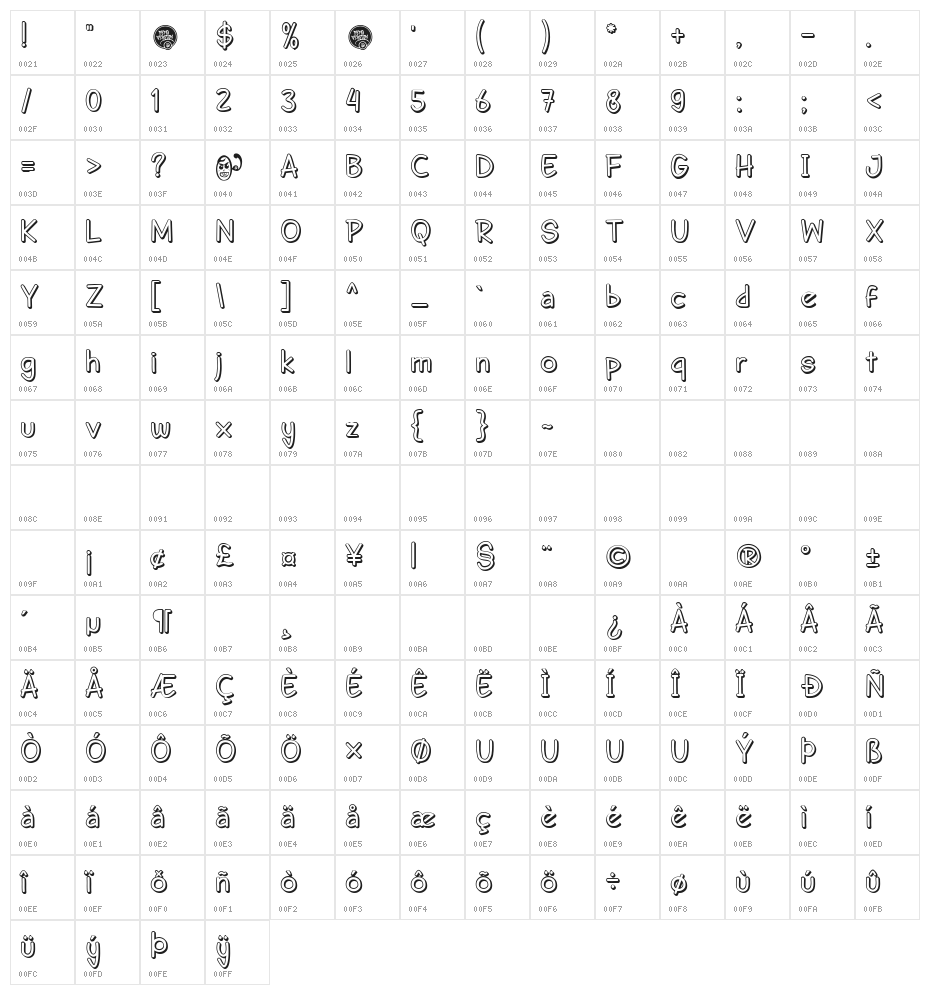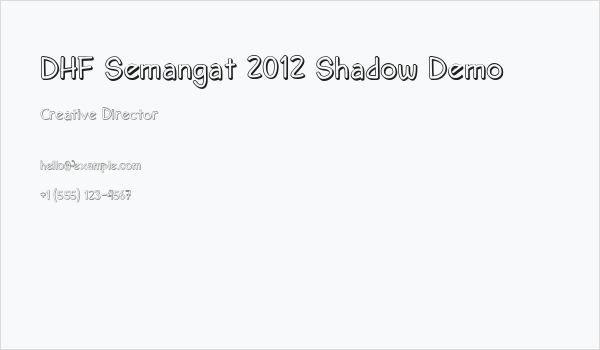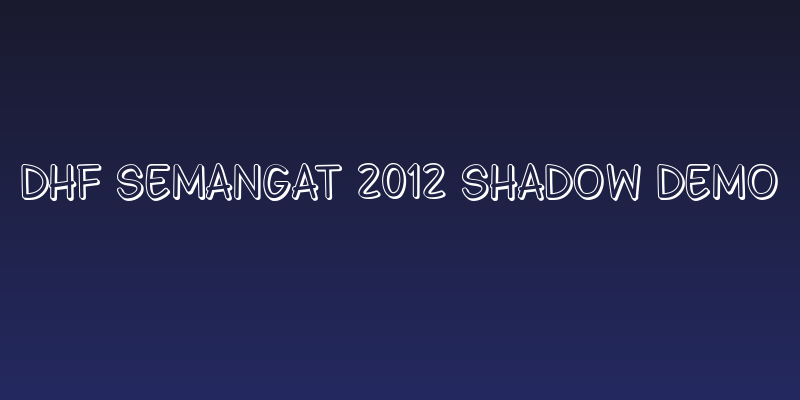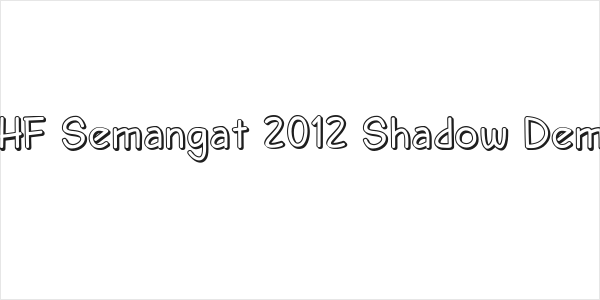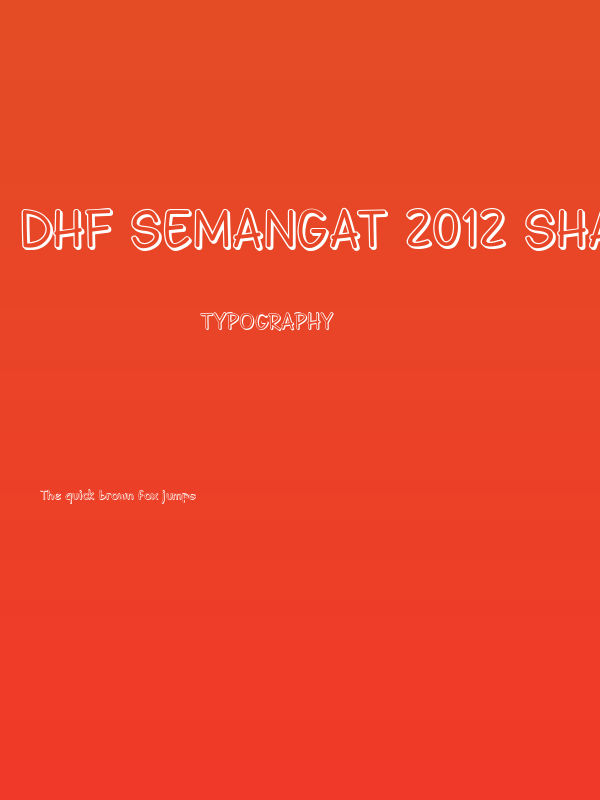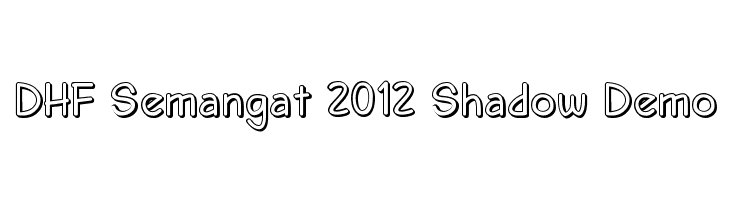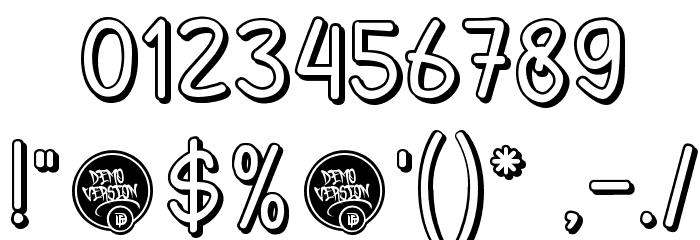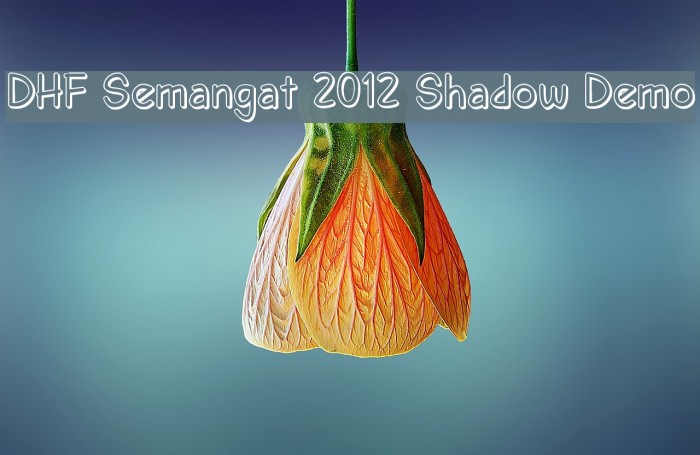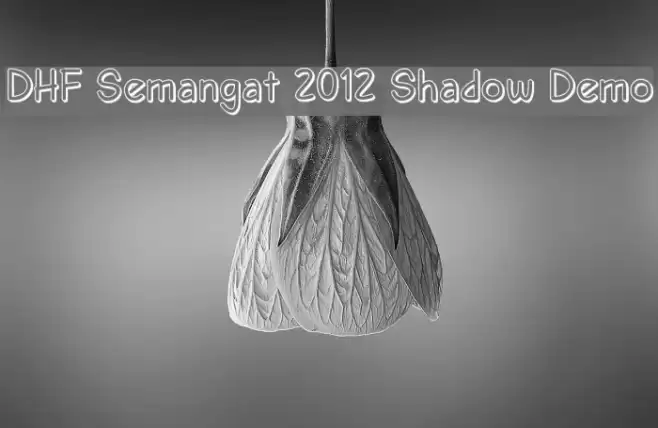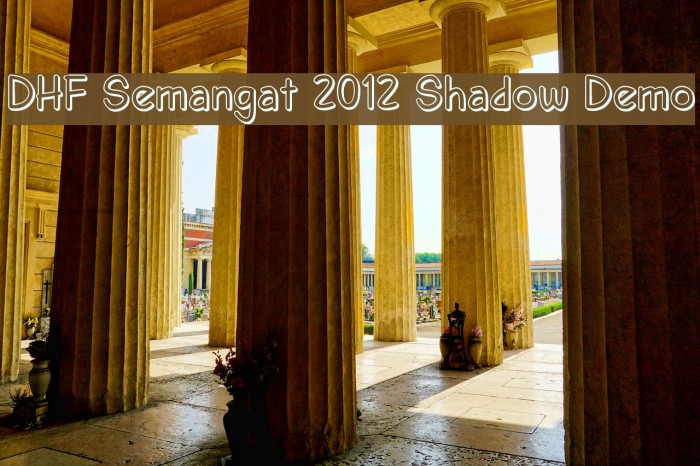
DHF Semangat 2012 Shadow Demo Font
| Vorgeschlagene Projekte | Ideal for children's book covers, playful posters, greeting cards, and any project requiring a fun and lively typeface. |